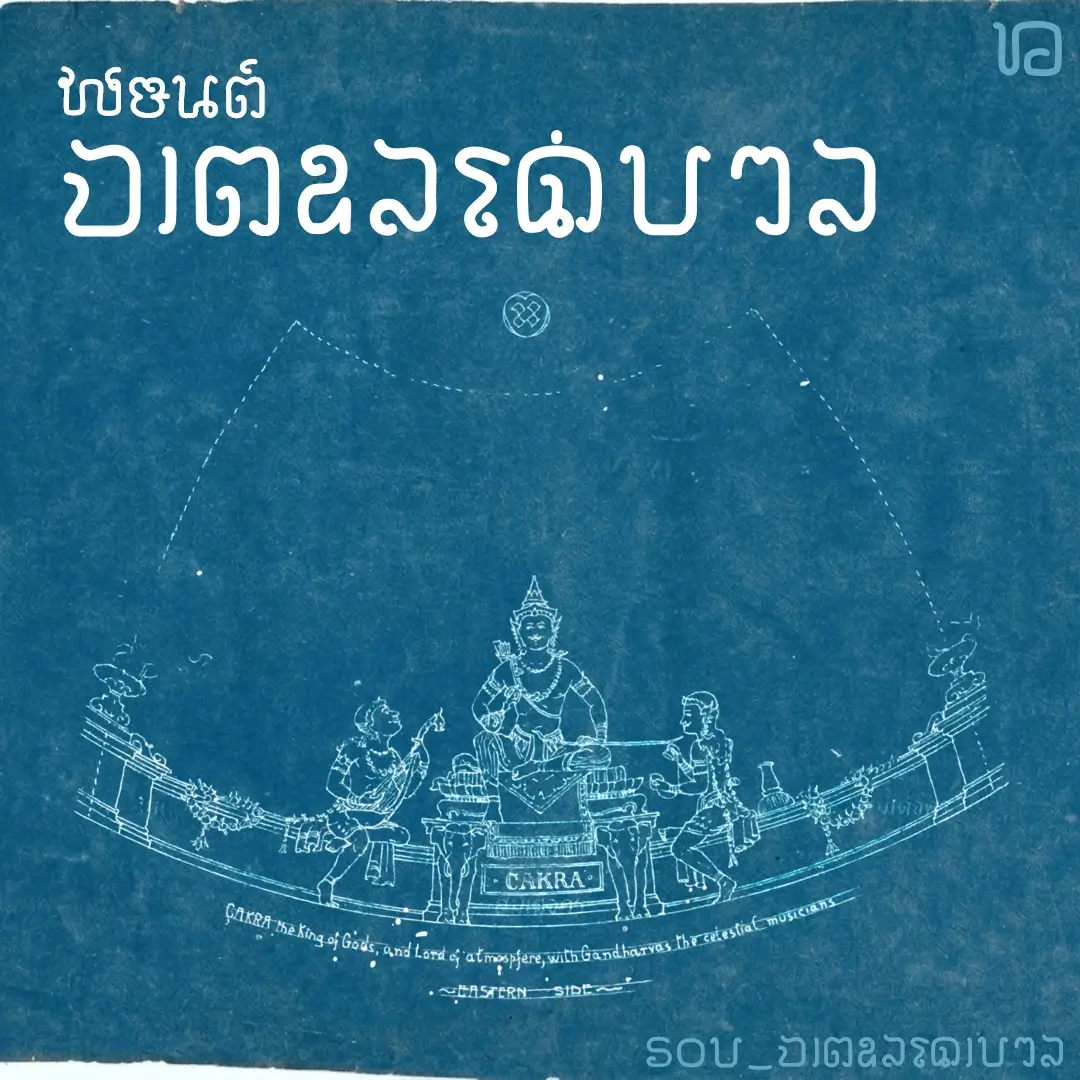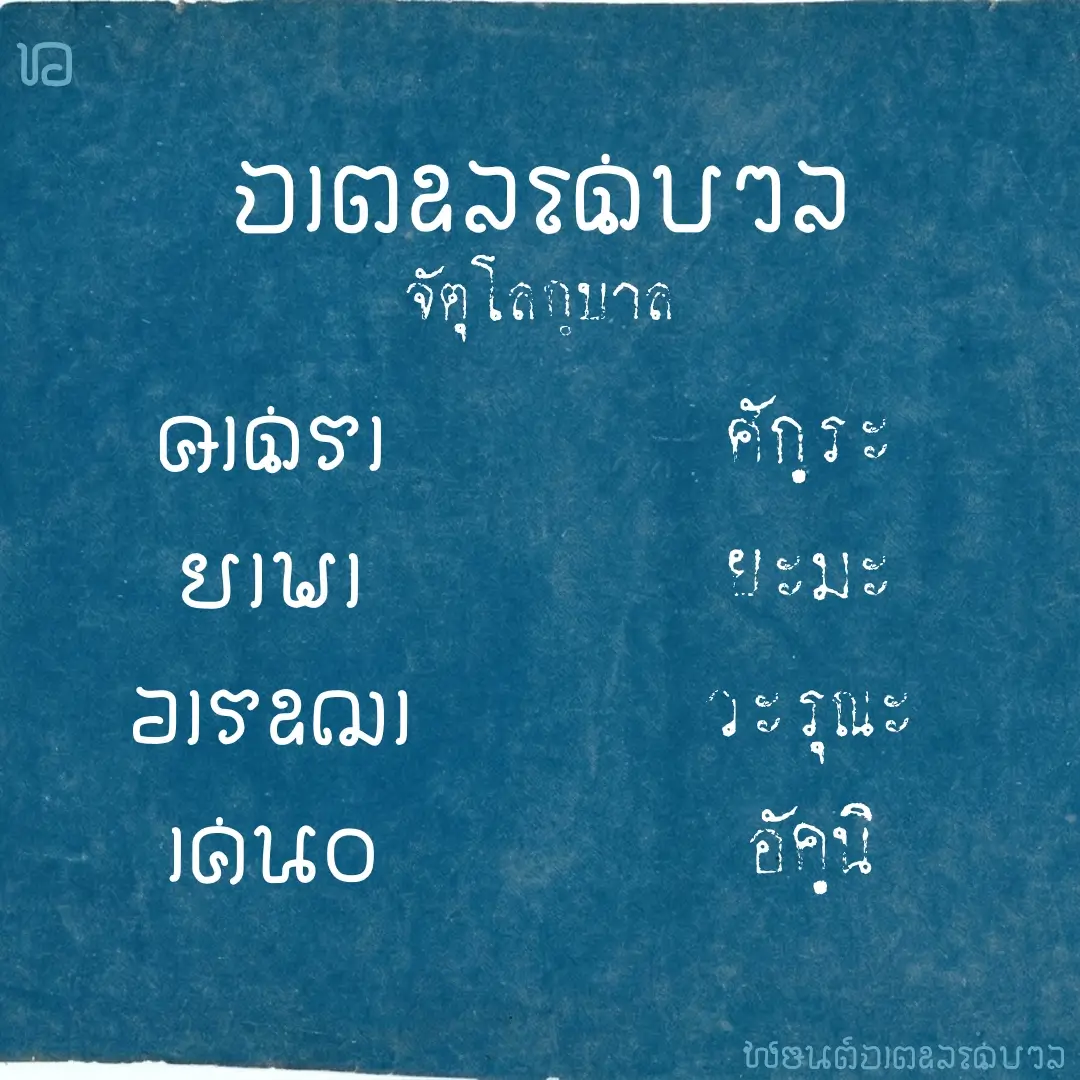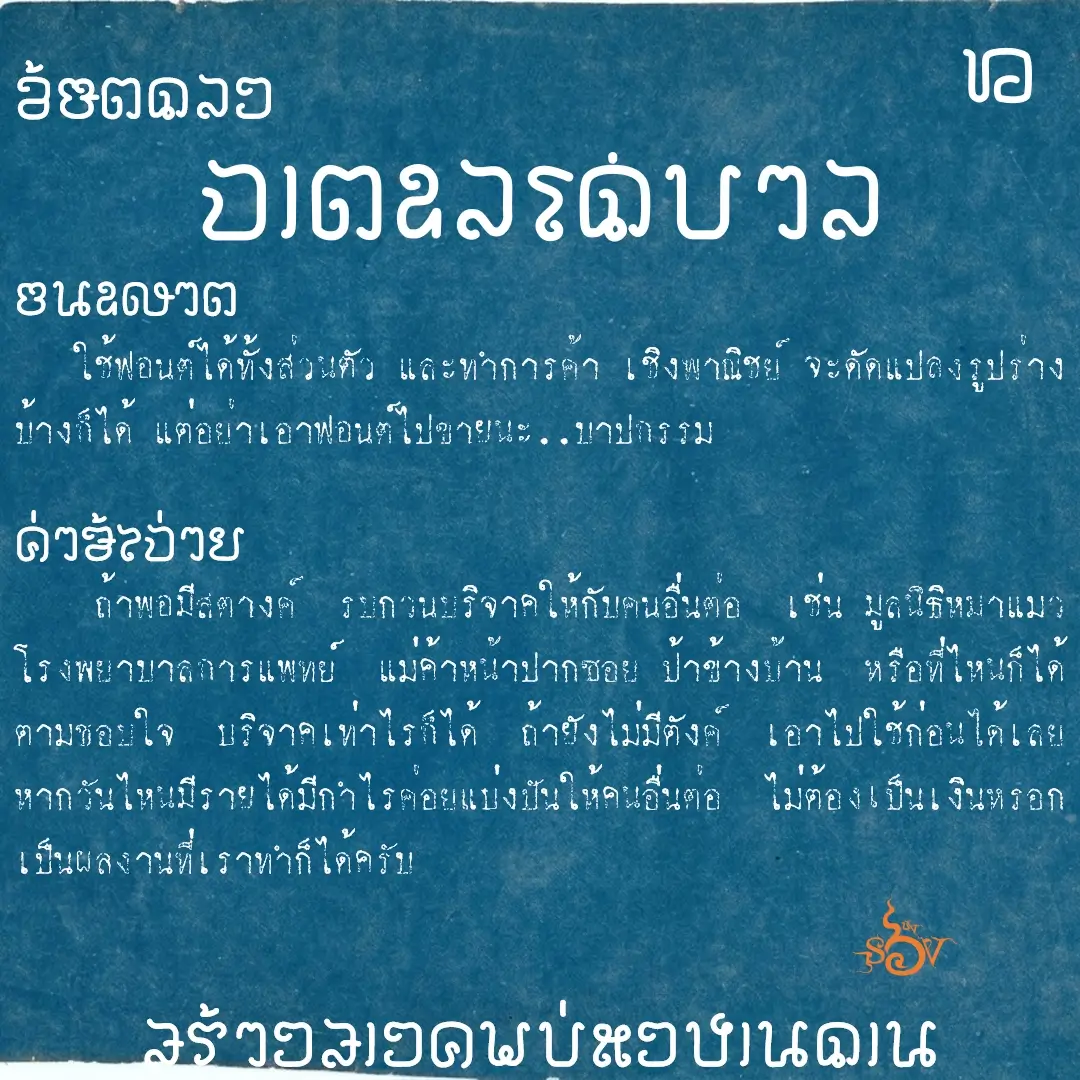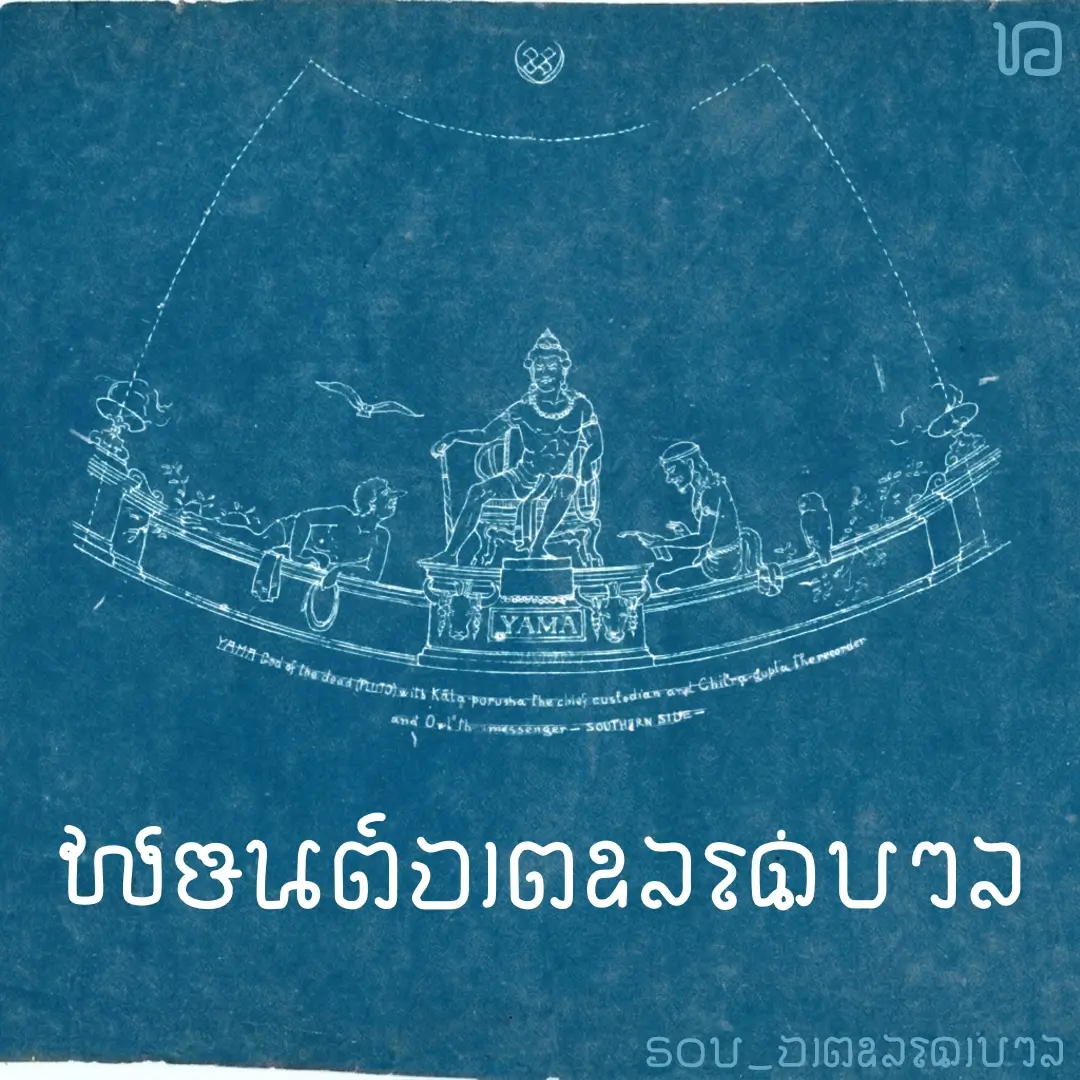
ฟอนต์นี้ได้แนวคิดจาก ตัวอักษรในภาพจตุโลกบาล ของสมเด็จครู ในพระที่นั่งบรมพิมาน พยัญชนะของพ่อขุนรามฯ สระและวิธีเขียนจากอักขรวิธีใหม่ของ ร.6 แต่พิมพ์แบบฟอนต์ไทยปรกติ เดี๋ยวฟอนต์จัดการสระให้เอง
ยกเว้นแต่สระลดรูป และอักษรควบ ต้องใช้พินทุช่วย(ดูจากรูปตัวอย่าง)
เบื้องหลังการออกแบบ : ฟอนต์ จตุโลกบาล
จตุโลกบาล (SOV_jatulokabAl)